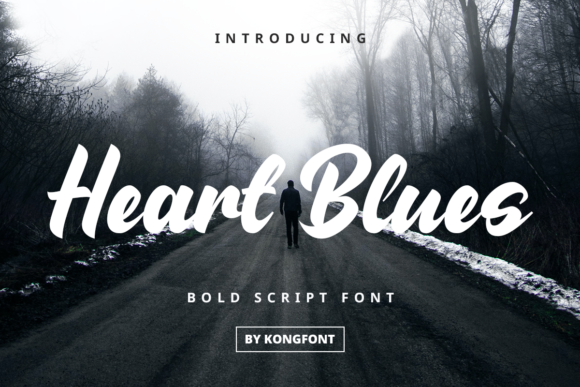
Heart Blues
หากคุณกำลังมองหาเนื้อหาคุณภาพสูงเช่น Heart Blues แพ็คเกจพรีเมียมนี้เป็นตัวเลือกที่ยอดเยี่ยมสำหรับโปรเจ็กต์สร้างสรรค์ของคุณ
ไม่ว่าคุณจะสร้างผลิตภัณฑ์ POD (Print on Demand) คำเชิญงานแต่งงาน หรือกราฟิกโซเชียลมีเดีย Heart Blues ก็เหมาะสมอย่างยิ่ง